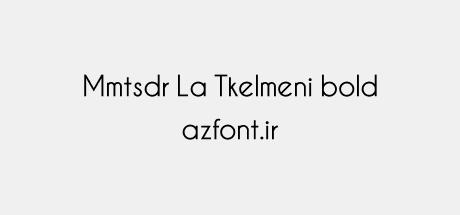
Mmtsdr La Tkelmeni bold
قلم زیبای Mmtsdr La Tkelmeni bold از سری قلم های بسیار زیبا برای تایپوگرافی و لوگو تایپ می باشد.این قلم در وزن Regular و توسط Mourad Boutros طراحی و منتشر شده است.